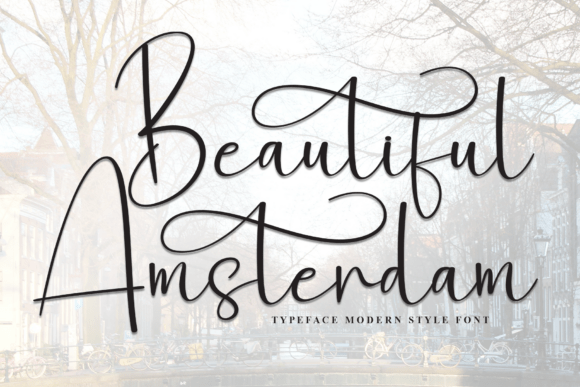
Beautiful Amsterdam
Pour sublimer votre souvenir de ce voyage, rien de tel qu’une typographie script élégante, comme le Beautiful Amsterdam font. Avec ses courbes fluides et ses swashes gracieux, ce style manuscrit ajoute une touche de sophistication à vos cartes postales, invitations ou publications sur les réseaux sociaux. Que vous créiez un logo personnalisé ou une citation inspirante, cette police donne à votre texte un charme romantique qui reflète parfaitement l’esprit d’Amsterdam.